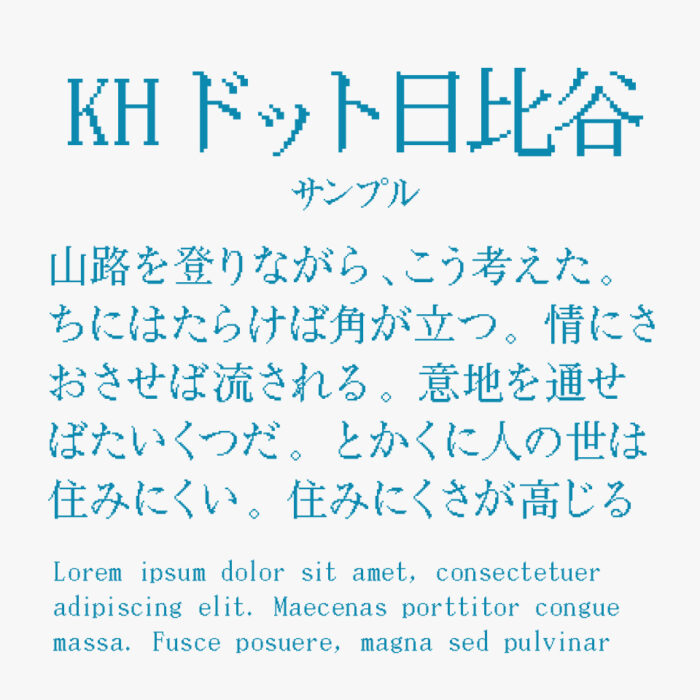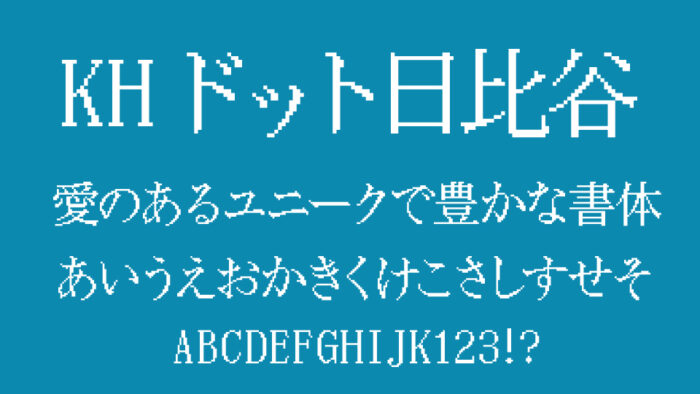
KHドット日比谷フォントは、書体デザイナーの平木敬太郎氏が1991年から1996年にかけてリリースされたフォントを再構成したドットフォントです。
KHドットフォントシリーズとして、「KHドット秋葉原」「KHドット神楽坂」「KHドット道玄坂」など地名を冠としてシリーズ展開されているドットフォントです。
その中でもKHドット日比谷フォントは、明朝体をベースとして作られているフォントです。
KHドット日比谷24・KHドット日比谷32の2タイプがあり、24と32ピクセル四方で作られています。